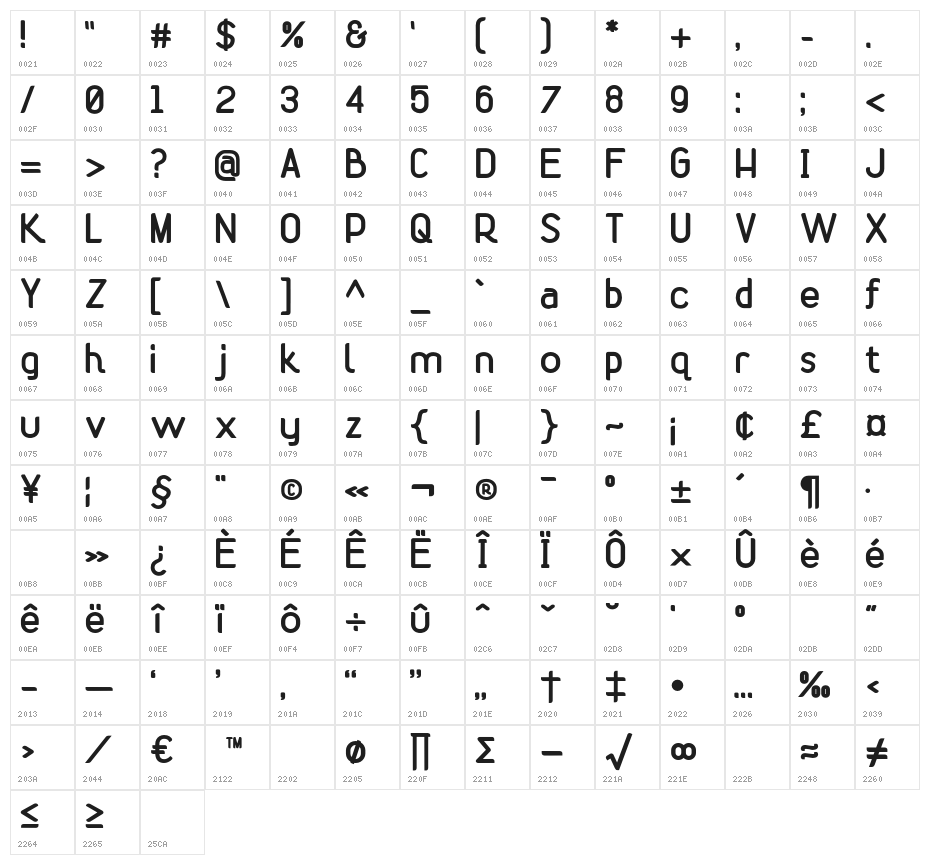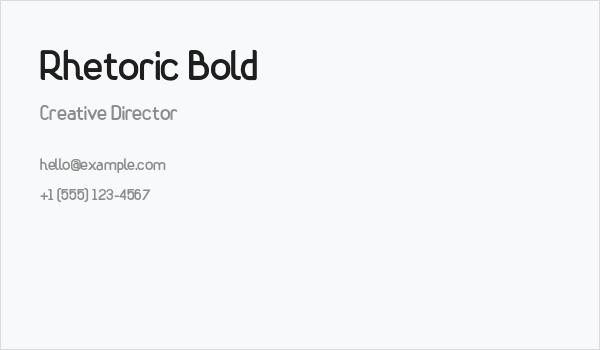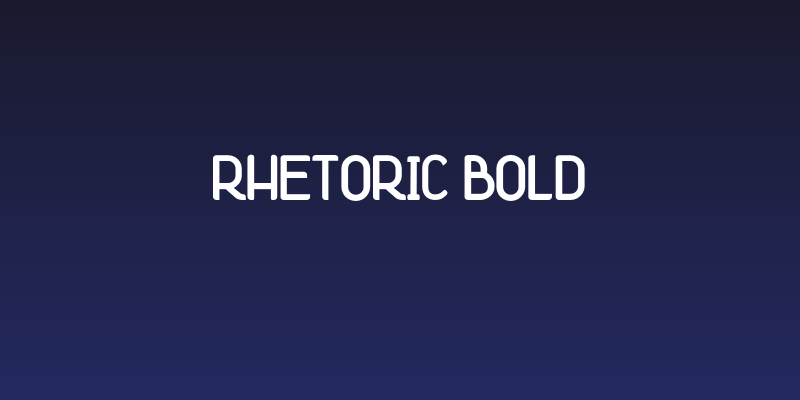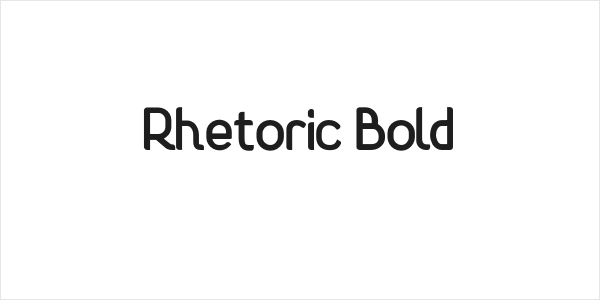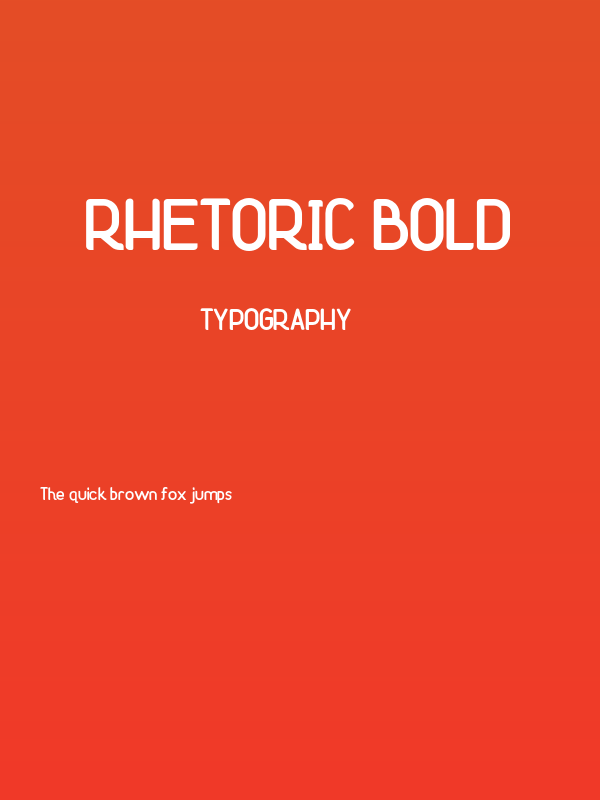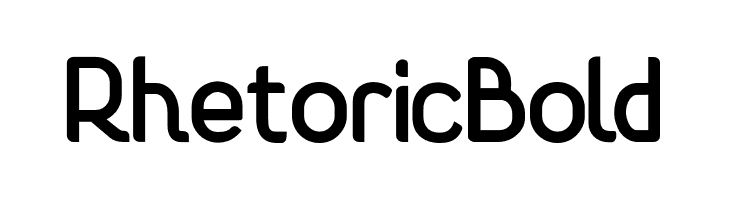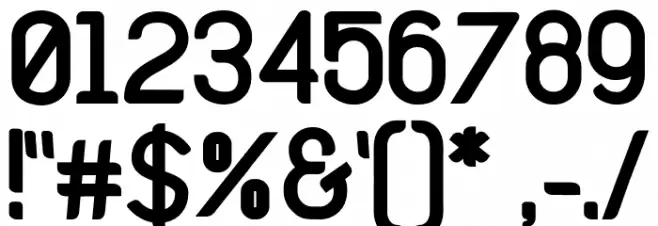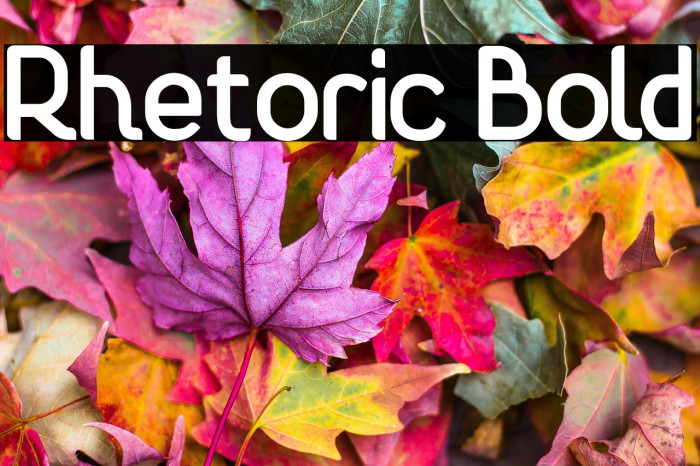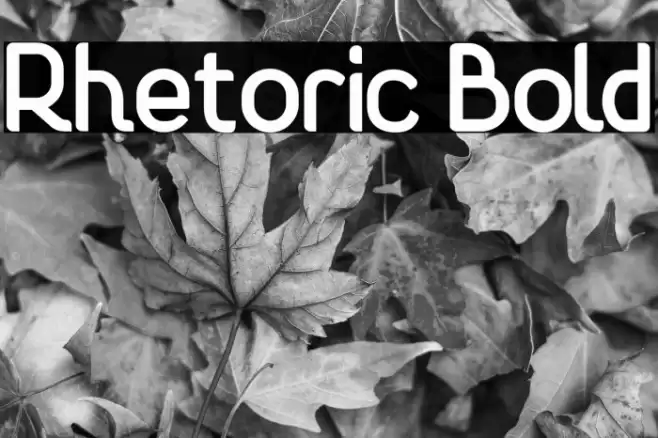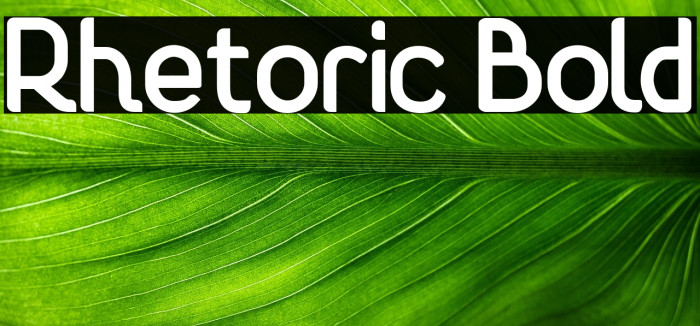
Rhetoric Bold Font
✎ Sans Serif
| Categorías | Sans Serif |
| Caso de uso | Headlines, Logos, Digital interfaces |
| Proyectos propuestos | Ideal for branding, advertising, headlines, and digital interfaces where a modern and approachable look is desired. |